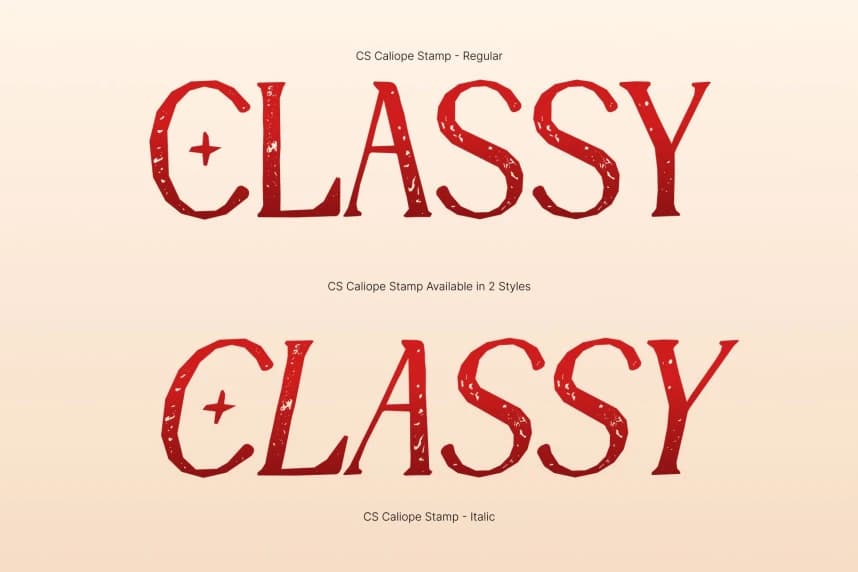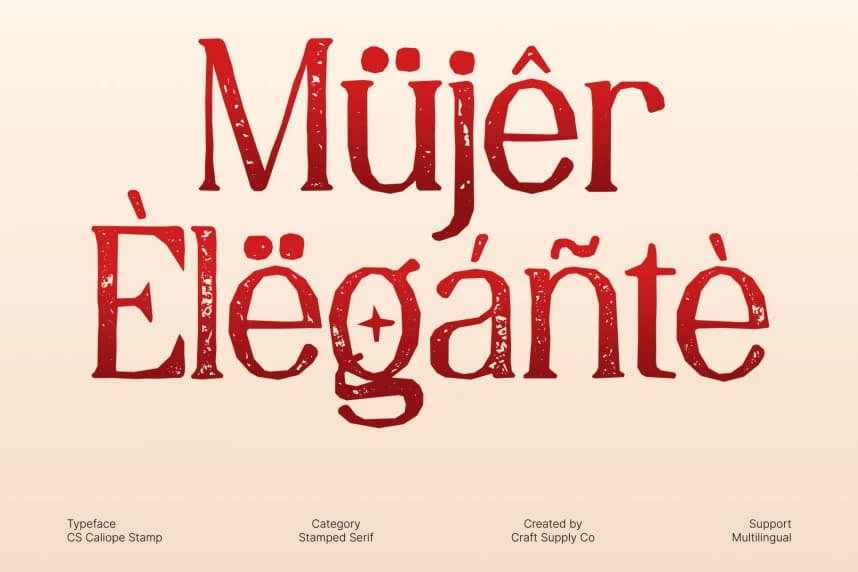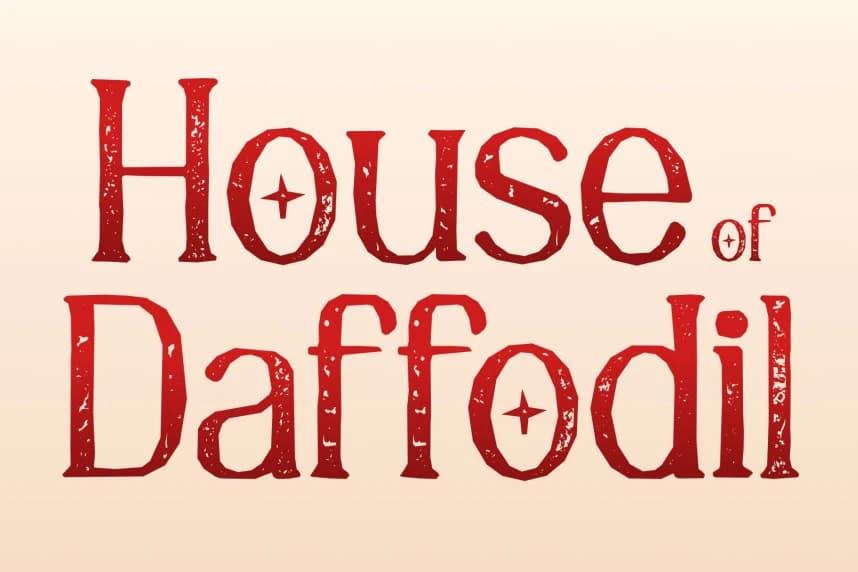
CS Caliope Damga Yazı Tipi
CS Caliope Stamp Font – Vintage Doku ile Uzatılmış Zarafet, Sanatsal Damga Karakterli Modern Serif. Bu, şık bir modern serifini dokunsal ve ifade dolu bir gösterim yazı tipine dönüştürür. Uzatılmış harf biçimleri zarif bir dikey ritmi korur.
CS Caliope Stamp Font – Vintage dokuyla uzatılmış zarafet, sanatsal damga karakterli modern serif. Bu, şık bir modern serifi dokunsal, ifadeli bir gösterim yazı tipine dönüştürüyor. Uzatılmış harf biçimleri zarif bir dikey ritmi korur
CS Caliope Stamp